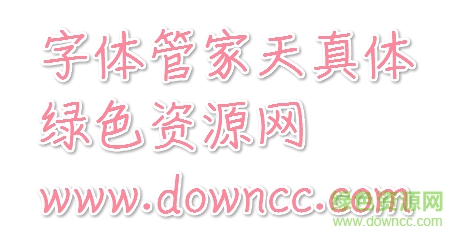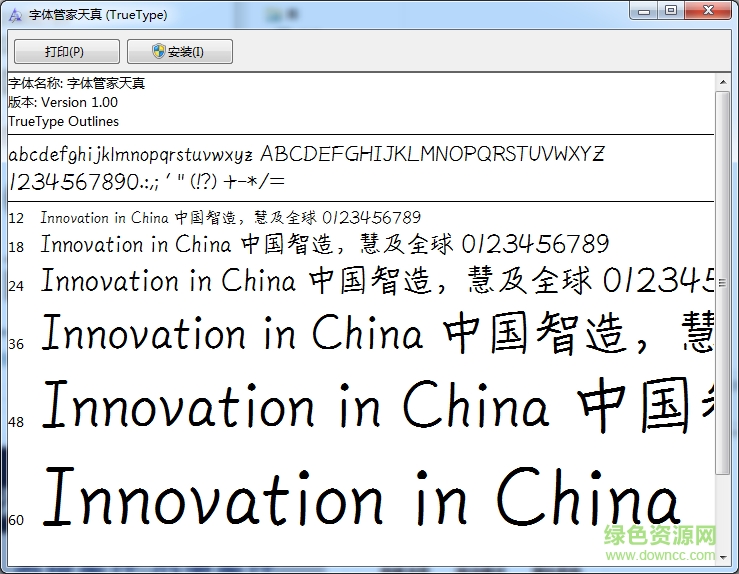
字體管家天真體是一款辨識度和清晰度比較高的常規(guī)手寫體,字跡柔和娟秀,給你比較舒適的視覺體驗,端正大方的造型讓你的藝術設計更有亮點,來綠色資源網(wǎng)即可免費體驗哦!
字體管家天真常規(guī)1.00字體,共有22604個字符。支持中英文和繁簡體書寫,讓你的海報設計、平面設計等更有獨家特色,是一款字體結(jié)構、顯示效果和風格都很不錯的藝術字體。